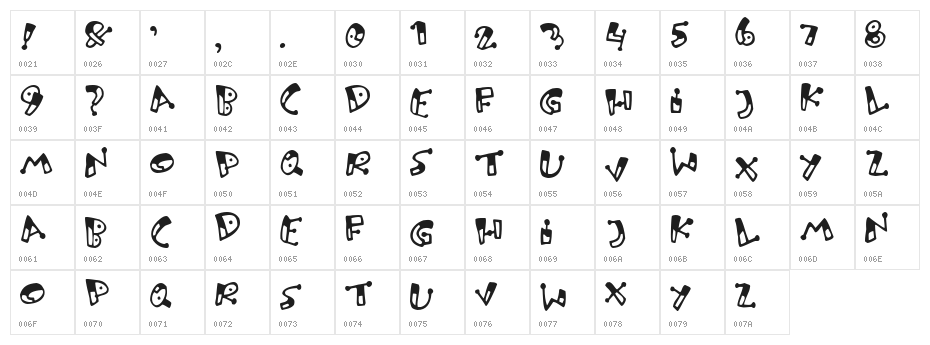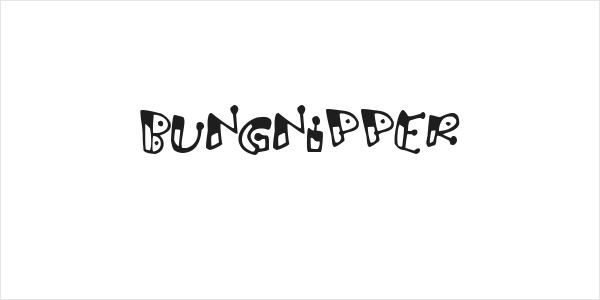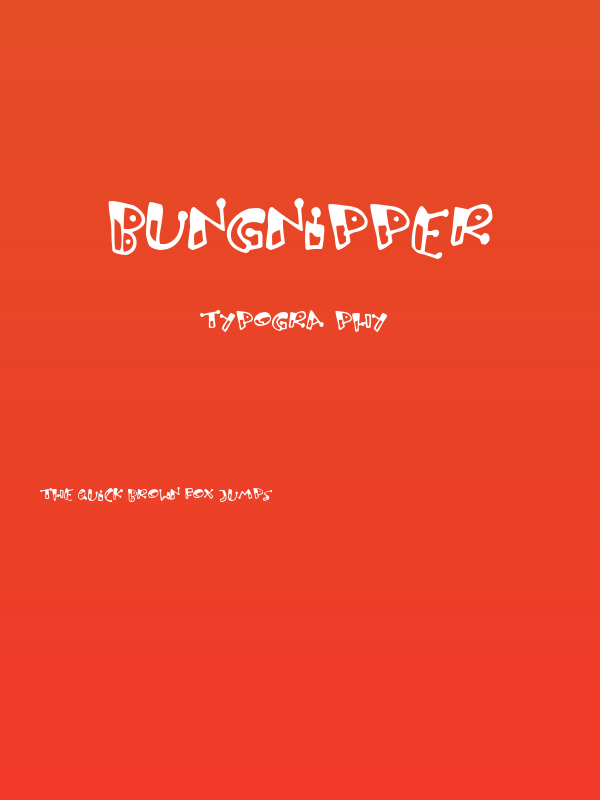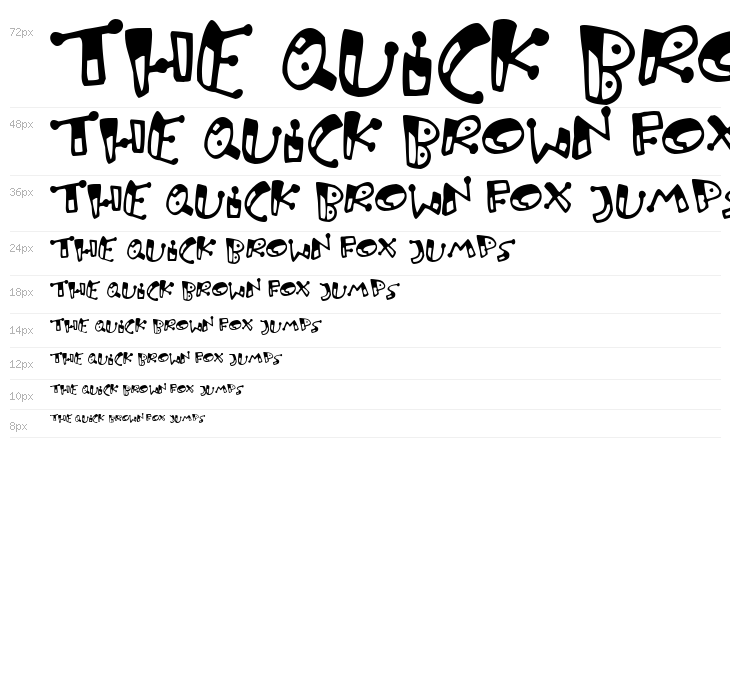
Bungnipper Font
✎ Quirky
Fonts by Uddi Uddi
| Progetti proposti | Ideal for children's books, playful branding, creative posters, and fun invitations. |